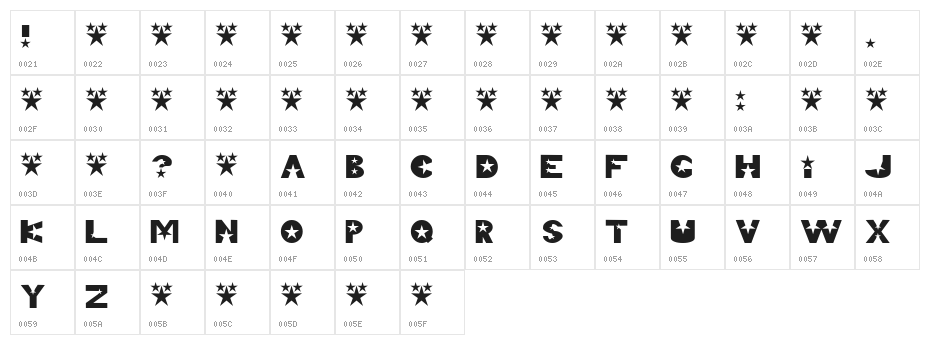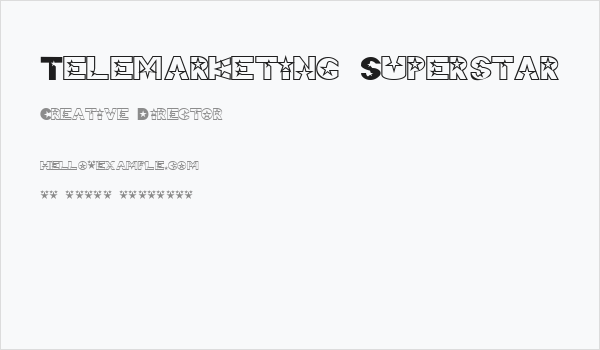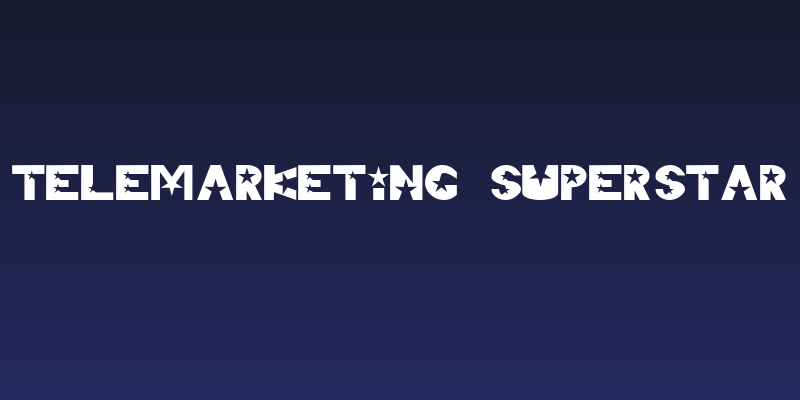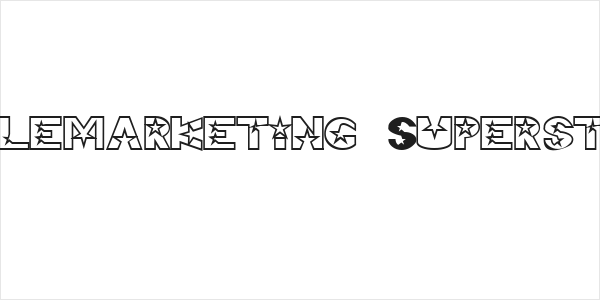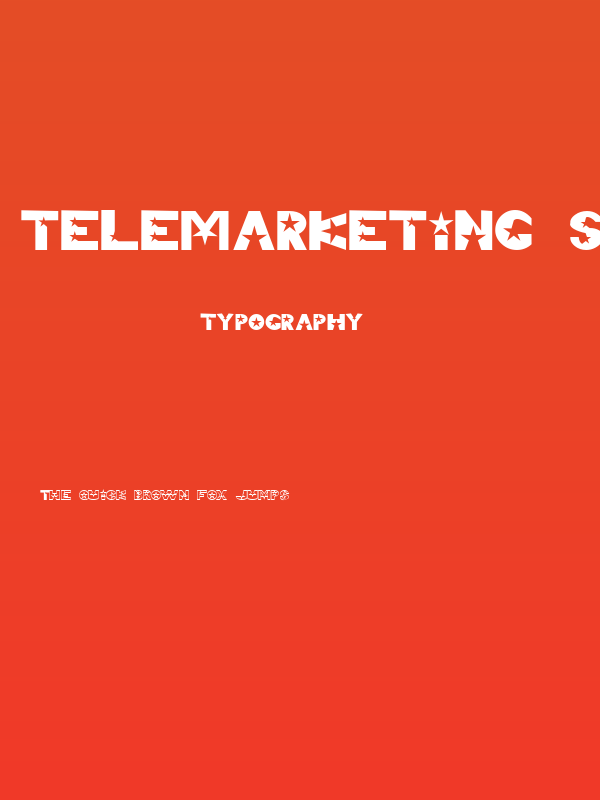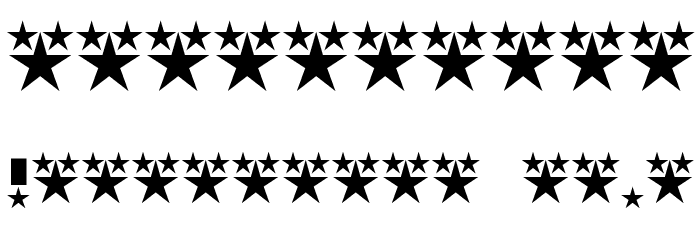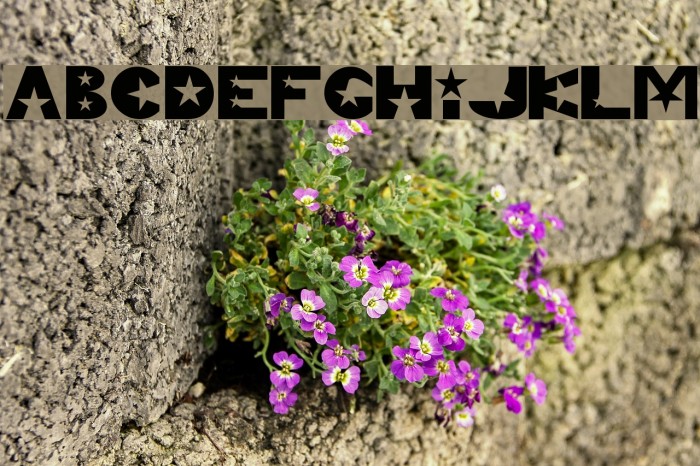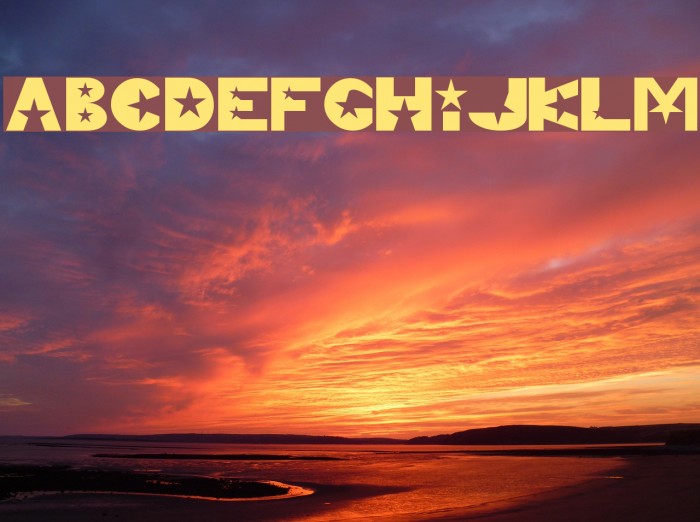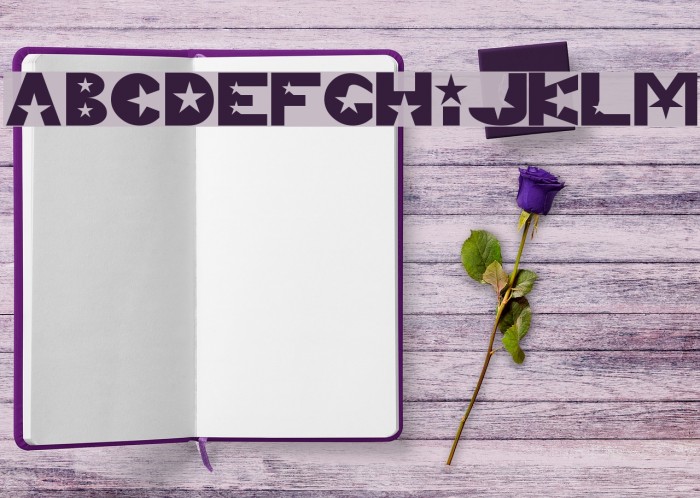
Telemarketing Superstar Font
| Projets proposés | Ideal for party invitations, event posters, children's book covers, or any project needing a playful, standout font. |